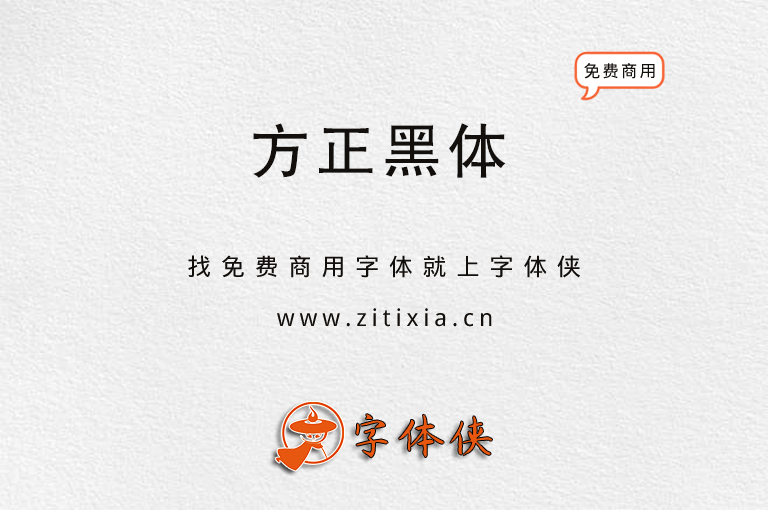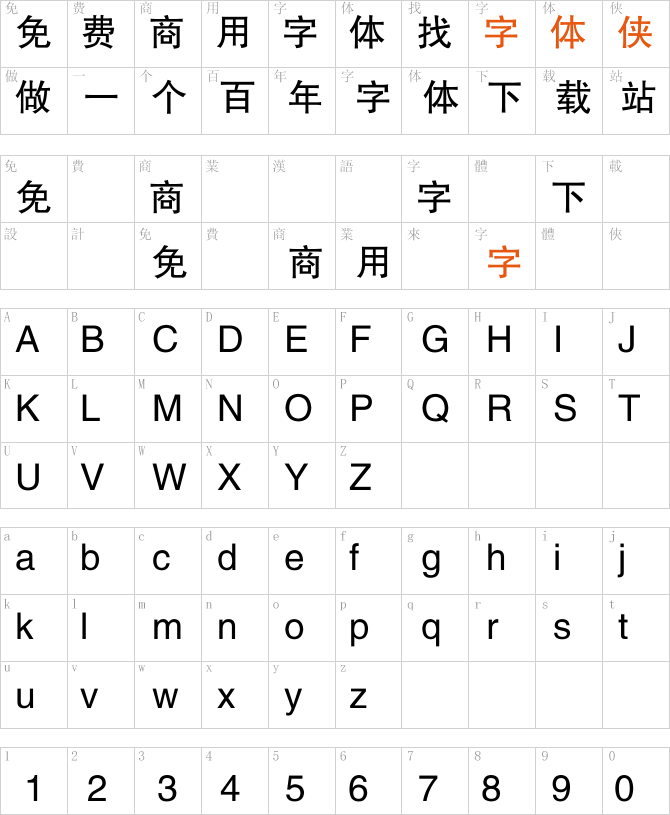
方正黑体字体缩略图:
方正黑体字体简介:
「方正黑体」源自上海印刷技术研究所为铅字印刷设计的字稿,是一款专门为正文排版设计的黑体。方正黑体的笔画两端留有喇叭口,撇、捺、钩笔画的粗细变化较大,中宫比较紧凑。其字重适中、字形风格中性朴实,不但适用于印刷媒介,还可用于屏幕阅读,是一款非常经典的正文黑体。
「方正黑体」的设计源于铅字时代的黑体字稿,是一款专门为正文排版设计的黑体。方正黑体的笔画两端留有喇叭口,撇、捺、钩笔画的粗细变化较大,中宫比较紧凑。其字重适中、字形风格中性朴实,不但适用于印刷媒介,还可用于屏幕阅读,是一款非常经典的正文黑体。
方正黑体映射图: